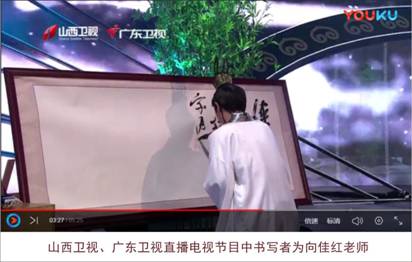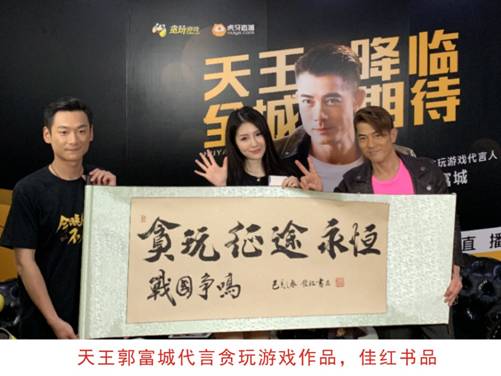
向佳红,1977年生于湖南溆浦,著名书法家、书法教育家、中国建设银行《龍》字书写者、《天山时报》党报报头书写者、华南理工大学特邀书法讲师、消防安全公益宣传片字幕书写者、监狱公益宣传片《逐风》片头书写者、广东卫视《国乐大典》特邀书法家、广东楹联学会会员、广东省文化学会会员、广州大学城文联顾问等。
成就与贡献: 中国建设银行 《龍》字标识 消防安全影院片(公益) 字幕 监狱公益宣传片《逐风》 片头 毕业后基金会 慈善捐赠
部分媒体报道:央视、广州新闻、今日头条、中国人物榜等
公益讲座(受邀院校): 华南理工大学、广东药学院、广东二师附中、广东二师附小、大学城穗石小学等,受益人数达上万人次。
与明星同台合作: 天王郭富城、歌星龚琳娜、李丽芬、马郁、演员康天庥等
向佳红简介
■ 向佳红,原名:向中华,著名书法家、书法教育家,1977年出生于湖南溆浦,是中国共产党唯一女创始人、第一任中央妇女部长、革命英烈向警予向氏后裔。 坚守传承,不忘初心,行走在公益的路上,用书写传递、用爱承载未来,央视、广州新闻、今日头条、中国人物榜等媒体曾专题报道。
■ 他自幼受家庭熏陶,沉迷书写,天当纸、指作笔,数十载如一日,笔耕不辍、诸体兼修,后又得名师指点,博采众长,研古出新,终成一体。尤行书见长,其字体“牵丝劲拔、秀逸多姿” 的神韵广受推崇,被誉为一款“神动而富有韵律”的行书。
■ 其楷书初学颜、柳,后又研习欧、赵,行书师法二王,再临米芾、黄庭坚等,字结构端庄,笔法严谨,又结合章草、融魏碑为一体,刚柔并济。其行书:即有楷书的端庄,又有草书神韵,楷中带行,行中见草,小字行云流水、笔走龙蛇、灵动飘逸;大字刚劲有力、气势磅礴、洒脱自然,风格变化万千,神采飞扬。
■ 几十年来,他一直从事书写工作,坚持只做这一件事,不断追求与探索字的美感,力求做到极致。曾多次参加大赛获奖并全国巡回展出,他的每一幅作品风格迥异、变化万千,耐人寻味,融入了他的思绪、情感,运笔如神、收放自如,书体大方流畅、自然而又不失书法本真韵味,虚实之间、粗细得体的线条,充分体现了他对中国汉字的认识、理解和结构把握,表达了他与众不同的审美观点。
■ 2013年10月,个人书法作品被收录电脑字体,命名为《向佳红毛笔行书》(非商业版),一经发布,好评如潮,深受网民疯狂下载并转载。2018年创作完成《中华金榜体》(非商业版),更是向老师炉火纯青之作。
■ 央视、银行(建行、大华银行、中信)、平安保险、名车(奥迪、东风)、贪玩游戏、出版社(南京大学出版社、山东人民出版社、山西人民出版社)、儿童剧《铠甲勇士捕将》等知名企业纷纷求字合作。
■ 登门拜师学艺的不计其数,其中有大学教授、书画老师、公司白领及外国学者等文人雅士等不远千里求师拜学,并受当地多家院校邀请开展书法讲座及参评工作,他将自己多年来悟出的习字乐趣经验分享,让厌学者在书写中找到快乐与自信,有基础者快速提高,受益人数达上万人次。
■ 近些年,他把全部精力投入到书法教育事业,积极参与社会公益事业,大力支持党政宣传,2018年他成立了佳红书品文化艺术,旨在传承发扬、育人育品。他曾为机关党报、党政刊物、公益宣传等免费书写,为社会做出了巨大贡献,并捐出多幅佳作慈善拍卖,所得收入全部捐献给贫困山区教育事业。